18 migliori font estetici 2023 (gratuiti e a pagamento)
Pubblicato: 2023-04-25Hai mai faticato a trovare il font perfetto per i tuoi progetti creativi? Sei stanco di usare gli stessi vecchi caratteri che usano tutti gli altri? Bene, sei fortunato perché oggi condivideremo i 18 migliori caratteri estetici che porteranno i tuoi progetti al livello successivo!
In questo articolo, presenteremo una varietà di caratteri unici ed eleganti che puoi utilizzare per qualsiasi cosa, dalla grafica dei social media ai materiali di branding.
Sapevi che la scelta del carattere giusto può aumentare la leggibilità fino all'80%? E con così tante opzioni là fuori, può essere travolgente scegliere quella giusta. Ecco perché abbiamo compilato questo elenco dei migliori caratteri estetici per semplificare il processo di selezione.
Senza ulteriori indugi, tuffiamoci nelle nostre migliori scelte per i migliori caratteri estetici! Sia che tu stia cercando un carattere di visualizzazione audace e spigoloso o un carattere di script delicato ed elegante, ti abbiamo coperto.
Quindi, diventiamo creativi e iniziamo a esplorare queste straordinarie opzioni di tipografia.
Migliori font estetici premium
Quindi, che tu stia lavorando a un progetto di branding, creando grafica per social media o progettando un sito Web, la nostra selezione dei migliori font estetici premium ti ispirerà sicuramente.
Immergiamoci ed esploriamo alcune fantastiche opzioni di carattere che porteranno i tuoi progetti al livello successivo.
Gemelli
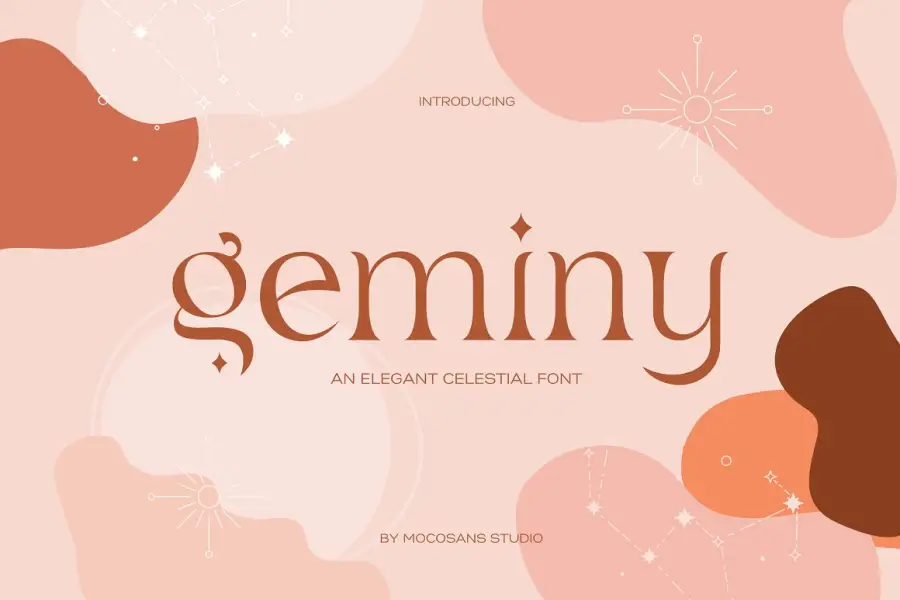
Gemini è un font moderno ed elegante che presenta un tocco di stile celestiale. Questo tipo di carattere è ideale per varie applicazioni come loghi, marchi, elementi artigianali, biglietti da visita, biglietti di auguri, biglietti di ringraziamento, adesivi, riviste, social media, inviti di nozze e pianificatore digitale e di stampe.
Il font Gemini è una scelta versatile ed elegante che può elevare qualsiasi progetto o design. Le sue linee e curve eleganti sono adatte per i design contemporanei, dove si desidera un look sofisticato. Il tocco celeste aggiunge un tocco unico al carattere, distinguendolo dagli altri caratteri della sua classe. Inoltre, è ideale per i caratteri estetici di Google.
Collinare
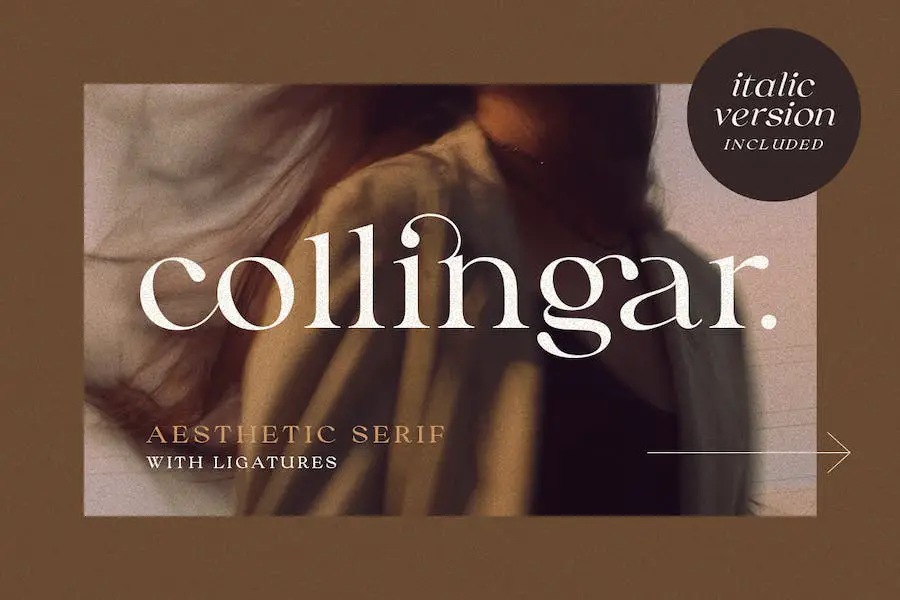
Colligar è un font serif versatile che combina elementi di design classici e moderni per creare un'estetica davvero unica. Ciò che distingue Colligar dagli altri font è la sua vasta collezione di legature, che consente ai designer di aggiungere un tocco in più ai loro poster, copertine o loghi.
La versione in corsivo del carattere può fungere da eccellente complemento a qualsiasi design, rendendolo un'ottima aggiunta alle tue raccolte di script.
Una delle caratteristiche distintive di Collingar è la sua capacità di stare da solo come font per vari scopi, inclusi gli inviti di nozze e il branding. Inoltre, è ideale per caratteri estetici eleganti.
Minakoe
Minakoe è uno straordinario font serif che trasmette un'aria di bellezza ed eleganza. È perfetto per chiunque desideri creare un logo o un design del marchio moderno, espressivo e femminile. Con le sue alternative e legature, puoi combinarle per creare il design tipografico perfetto per i tuoi prossimi progetti.
Questo tipo di carattere è altamente versatile e adatto a un'ampia gamma di applicazioni, tra cui loghi e marchi di lusso, design editoriale di classe, riviste femminili, marchi di cosmetici, promozione della moda, branding di gallerie d'arte, musei ed eventi storici o architettonici. È perfetto per i caratteri alla moda angolari.
Estetica belga
Belgan Aesthetic è un font che può migliorare l'aspetto visivo di qualsiasi progetto, che si tratti di loghi o marchi, inviti, post sui social media o design di prodotti. Il suo stile unico aggiunge un tocco artistico al tuo lavoro e lo distingue dalla massa.
Il font è ideale per chi desidera un look sofisticato ed elegante, in quanto presenta lettere ornate con un tocco classico. È perfetto per creare progetti di matrimoni, cancelleria, citazioni stampate e confezioni di prodotti, utilizzando i caratteri estetici per Instagram.
Domenica romantica
Sunday Romantic è un font serif condensato che trasuda raffinatezza ed eleganza, rendendolo ideale per varie forme formali come inviti, etichette, loghi, riviste, libri, biglietti di auguri o di nozze, moda o qualsiasi scopo pubblicitario. Lo stile unico di questo carattere tipografico aggiunge un ulteriore livello di fascino a qualsiasi design, distinguendolo dagli altri.
Il design sottile ed elegante del carattere lo rende perfetto per i progetti che richiedono un layout più compatto senza sacrificare l'eleganza. Le curve eleganti e gli spigoli vivi di ogni personaggio si completano a vicenda per creare un look bello e armonioso che sicuramente impressionerà. Sarà l'ideale per i caratteri delle carte estetiche.
Hoistek